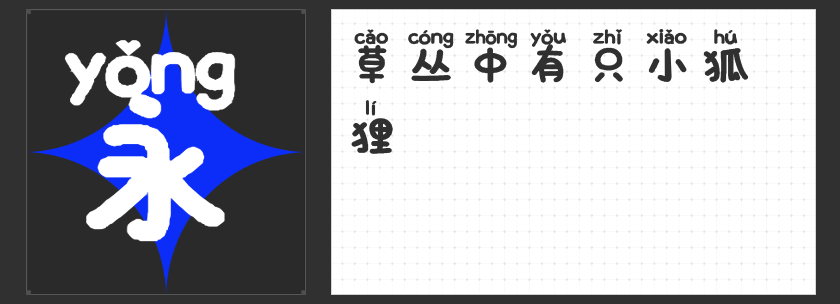
四款印刷字体推荐:匠心设计赋予文字独特魅力
在印刷设计中,字体的选择不仅是信息的载体,更是视觉美学的灵魂。本文精选四款风格迥异的优质字体,从现代锐利到童趣温暖,从高雅格调到灵动萌趣,为不同场景的印刷设计提供多元选择。
一、励字钧线黑简 微黑
这款字体以全直线设计突破传统黑体的圆润框架,笔画转折利落如刀削,斜度精准到毫米级,赋予文字强烈的工业美学气质。设计师通过细节优化消除视觉冗余,在保持锐利棱角的同时降低阅读疲劳感,尤其适合科技品牌手册、建筑展览图册等需要传递专业性与现代感的场景。其独特的结构语言能瞬间抓住观者视线,成为画面中的视觉焦点。
二、字圈也字绘本拼音体
专为儿童读物打造的这款字体,将拼音注音与汉字设计完美融合。字形采用圆润无棱角的曲线,每个笔画都像被赋予了弹性,搭配活泼的拼音字母布局,营造出天真烂漫的视觉氛围。在低幼绘本、识字卡片等印刷品中,其可爱形态既能吸引儿童注意力,又能通过拼音辅助提升阅读体验,让文字与图像共同构建沉浸式学习场景。
三、励字憨憨简
以“呆萌”为设计核心的励字憨憨简,通过大量圆弧形笔画消解了汉字的方正感。字形如气球般饱满充盈,笔画粗细对比强烈却保持整体协调,仿佛每个字都在传递欢快情绪。这款字体在儿童主题公园导视系统、节日促销海报等场景中极具表现力,其强烈的装饰性既能活跃版面气氛,又能通过视觉语言精准触达目标受众的情感需求。
四、高手兵克高雅宋
这款字体以传统宋体为基底,通过拉长字形比例重塑优雅气质。笔画纤细如竹,横竖转折处保留了宋体特有的顿挫韵味,却又以更修长的结构打破沉闷感。在文化杂志封面、高端艺术品图录等印刷品中,其清瘦身姿与留白空间相得益彰,既能承载深厚文化内涵,又能通过现代审美演绎东方美学精髓,成为提升版面格调的利器。
励字钧线黑简 微黑适合追求先锋设计感的商业印刷;字圈也字绘本拼音体是亲子类出版物的理想之选;励字憨憨简能瞬间点亮儿童主题场景;高手兵克高雅宋则为文化类印刷品注入诗意气质。四款字体虽风格迥异,却共同展现了字体设计在信息传递与美学表达间的精妙平衡。